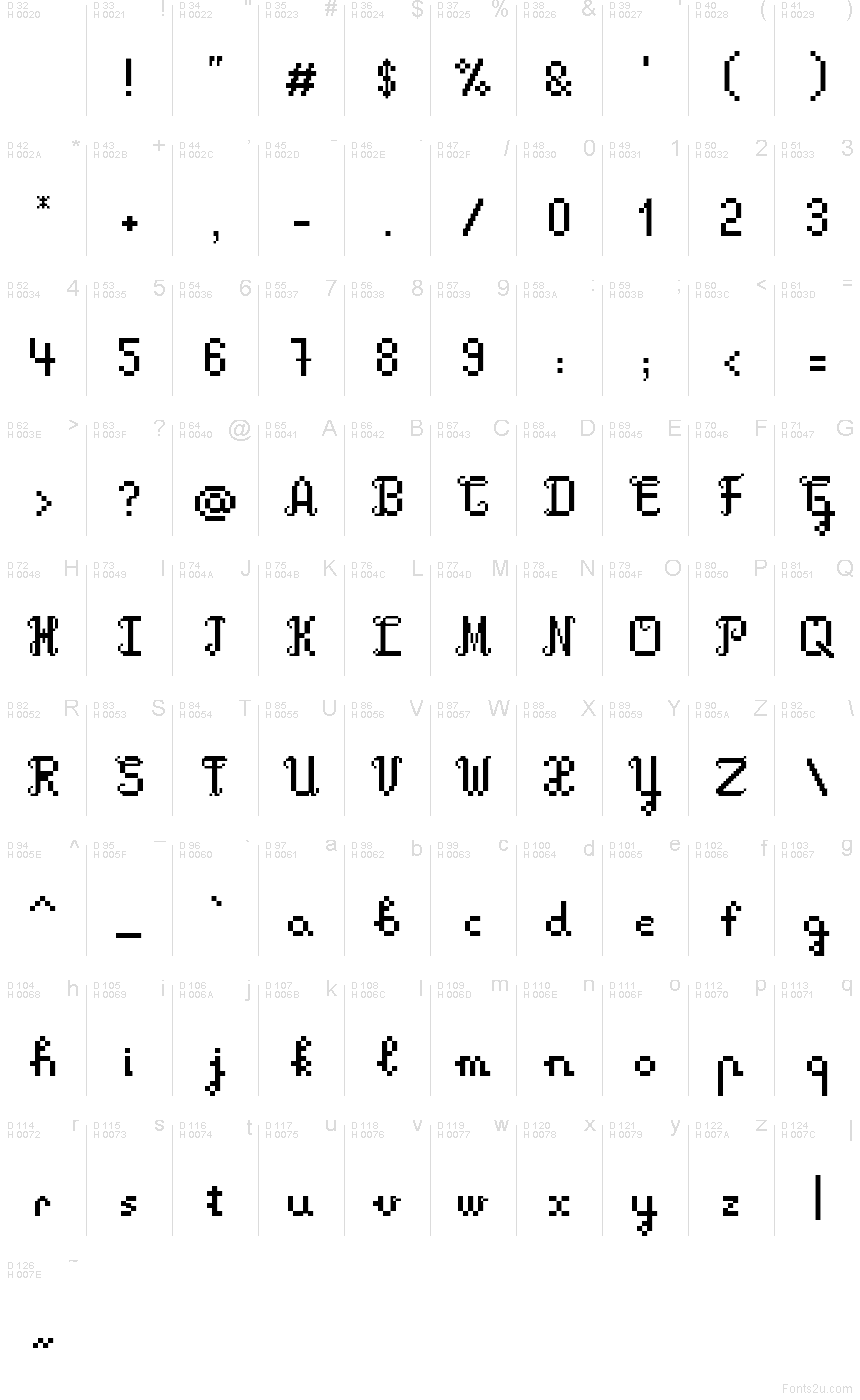
XoanXoan Vnmexel MacDinh di Vuong Tran Kamerua è un carattere bitmap pixel gratuito dal mood giocoso arcade-folk. Le lettere sono costruite con blocchi quadrati e corposi, ma gli angoli che ricordano dei germogli e i piccoli raggruppamenti impediscono un aspetto freddo, conferendo al carattere un tocco artigianale, tipico delle mappe di gioco.
Si adatta perfettamente a loghi di giochi rétro, titoli di poster, copertine di fanzine, grafiche per sticker e brevi intestazioni di interfacce dove quel ritmo irregolare può fare la differenza. Essendo un font gratuito, è ideale anche per titoli, overlay per stream e brevi progetti di branding, specialmente se cerchi una struttura pixel con un tocco ornamentale.